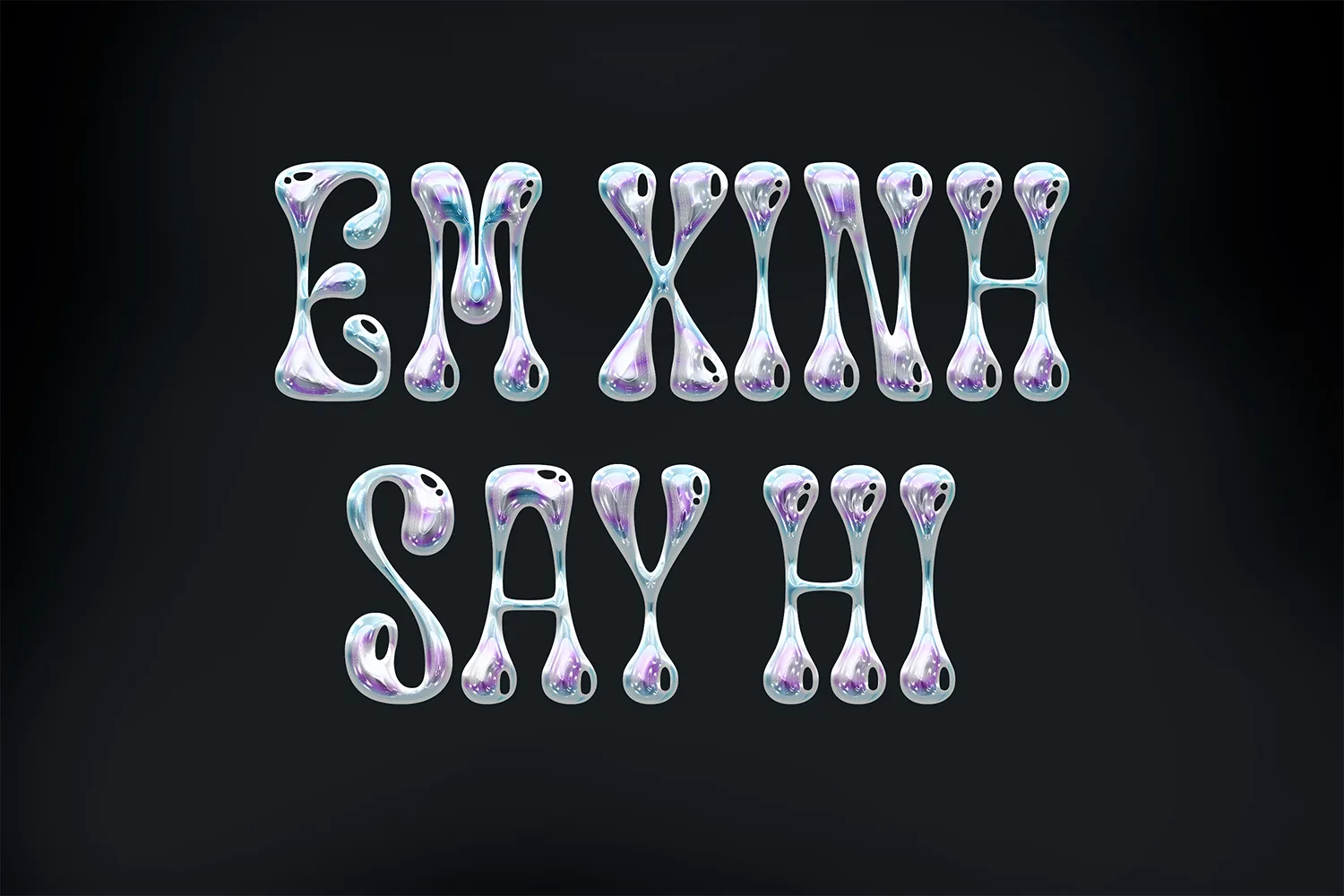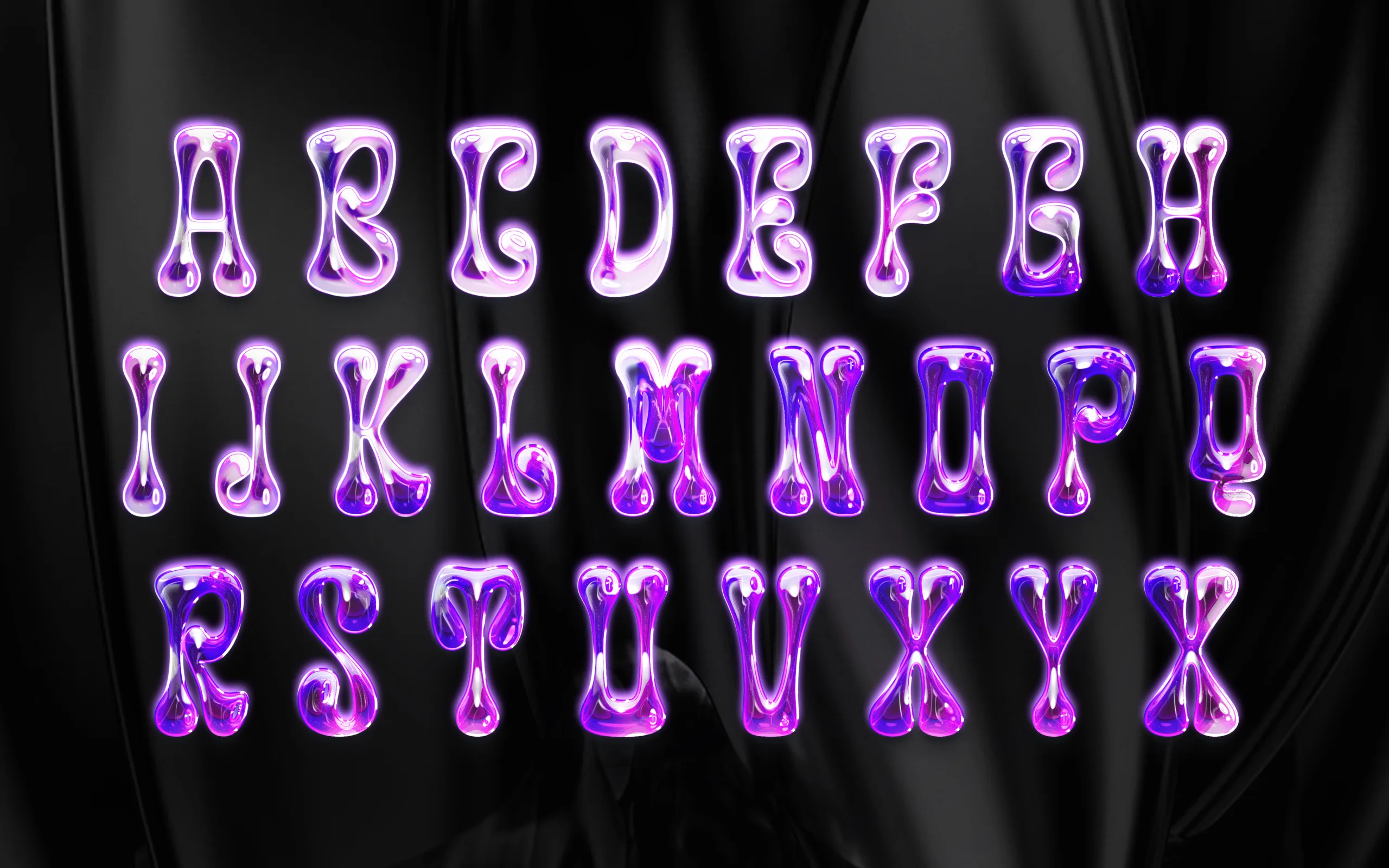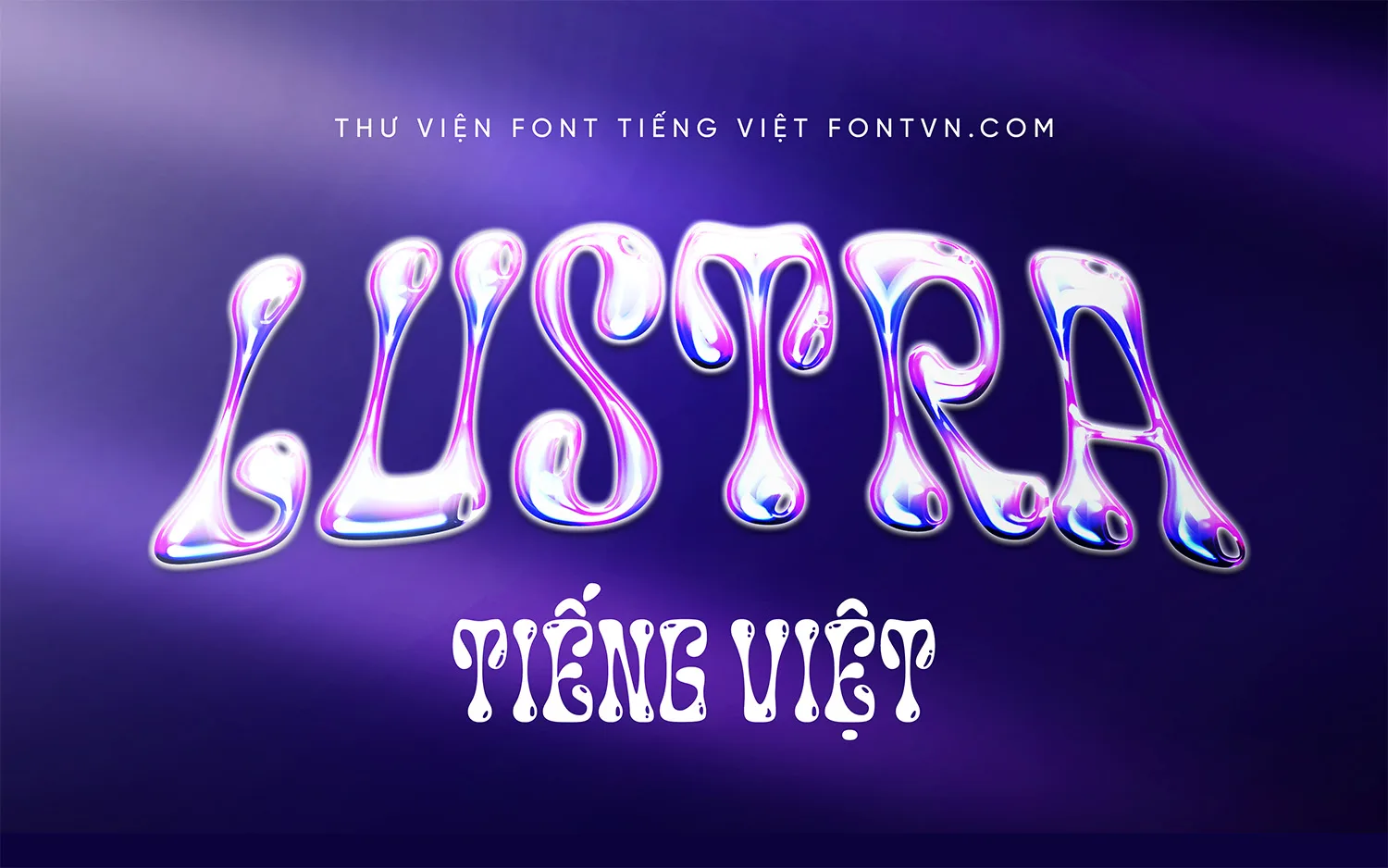
DVN Lustra tiếng Việt – Font chữ dạng chất lỏng xu hướng Y2K
DVN Lustra Việt hóa – Font chữ mang phong cách liquid glass hiện đại, phản chiếu ánh sáng như thủy tinh tan chảy. Nét chữ mềm mại, bóng mịn, kết hợp hiệu ứng chuyển sắc tím – xanh – hồng đặc trưng của xu hướng Y2K mang đến cảm giác tương lai pha lẫn hoài niệm.
Với hình dạng linh hoạt như chất lỏng và độ bóng tựa ánh kim, DVN Lustra đặc biệt phù hợp cho thiết kế tiêu đề, poster âm nhạc, visual thời trang, bìa album, giao diện kỹ thuật số hoặc ấn phẩm mang phong cách retro-futuristic.
Đây là kiểu chữ dành cho những nhà sáng tạo muốn thổi làn gió lấp lánh, ảo diệu vào tác phẩm của mình — nơi từng con chữ như đang tan chảy dưới ánh sáng neon.